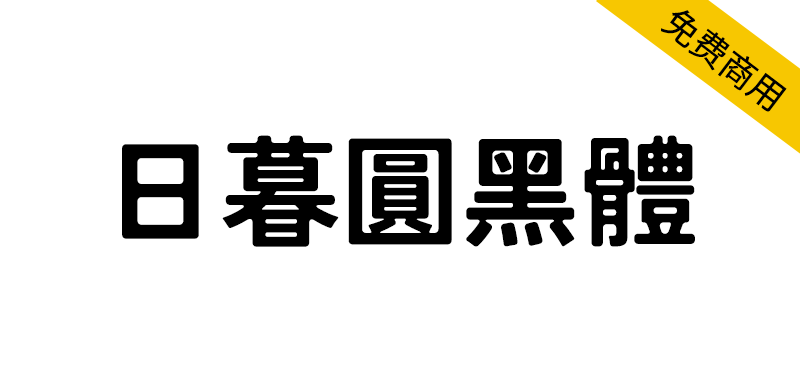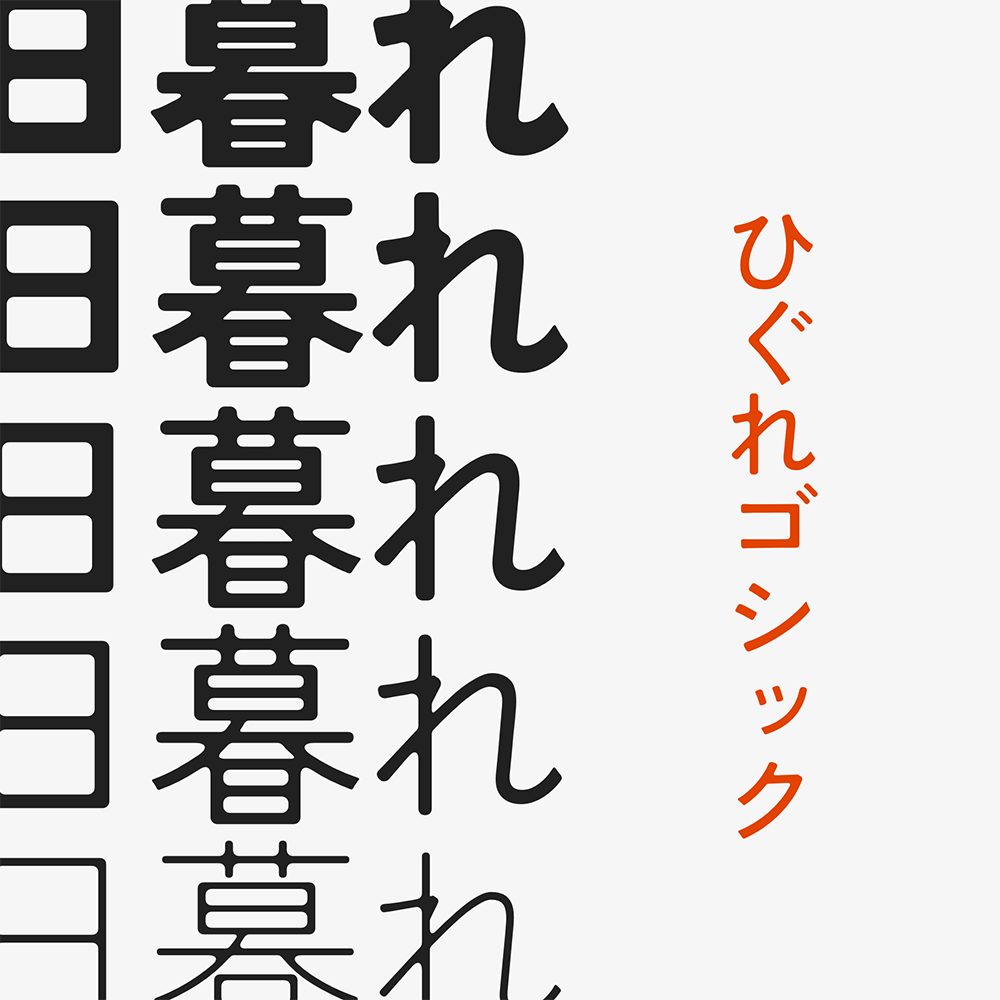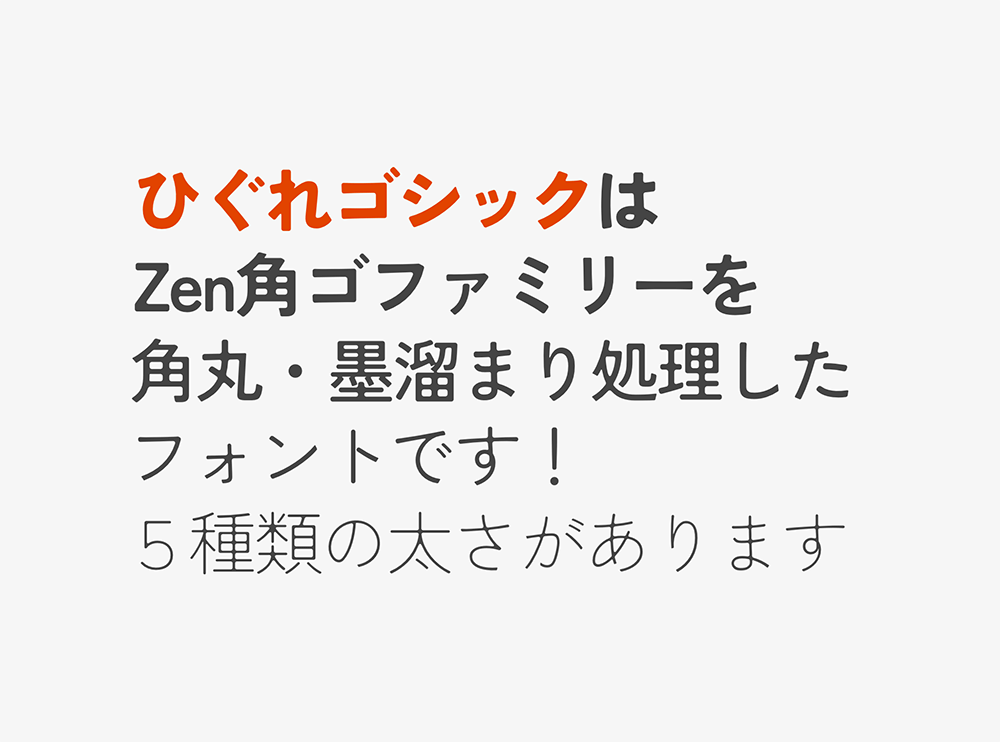
【日暮圆黑体】基于Zen角黑体进行圆角化与墨韵处理而成
日暮圆黑体(ひぐれゴシック)是基于 Zen角黑体 进行圆角化与墨韵处理而成。采用SIL开源字体授权协议发布,无论个人或商业用途均可免费使用。因采用自动化处理工艺,部分笔画可能存在处理不够精细的情况。本字体是在Zen角黑体基础上二次创作而成,特此向原始字体开发者致以诚挚谢意。